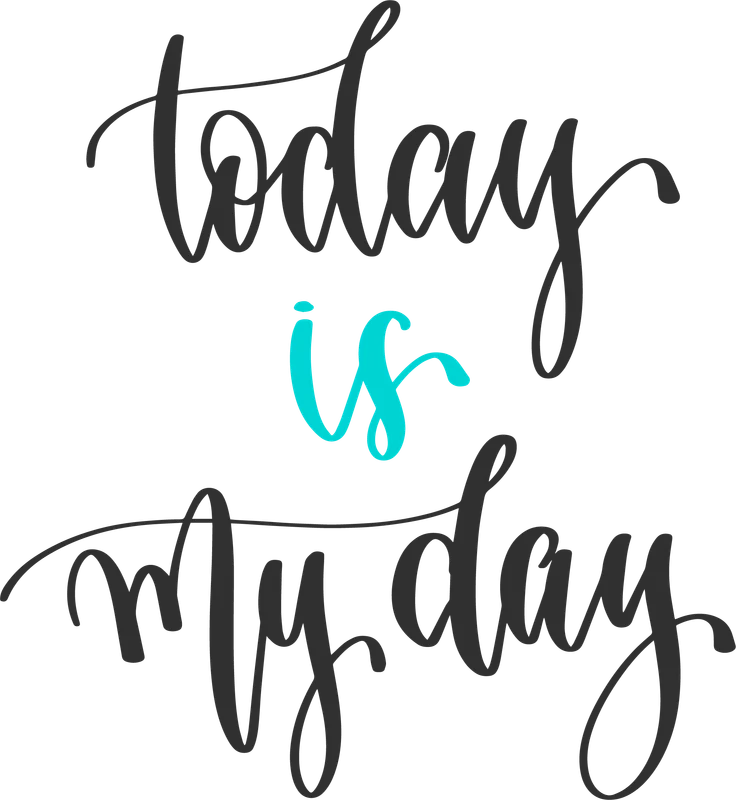
Thông điệp tích cực "Today is My Day" font chữ đẹp
Thông điệp tích cực "Today is My Day" font chữ đẹp — Truyền cảm hứng tích cực với thiết kế "Today is My Day" font chữ calligraphy. Phù hợp in áo thun, túi tote, quà tặng.
Trong hình có: chữ viết, slogan
Phong cách: calligraphy · Cảm giác: vui
Tông màu chủ đạo: xám, xanh ngọc